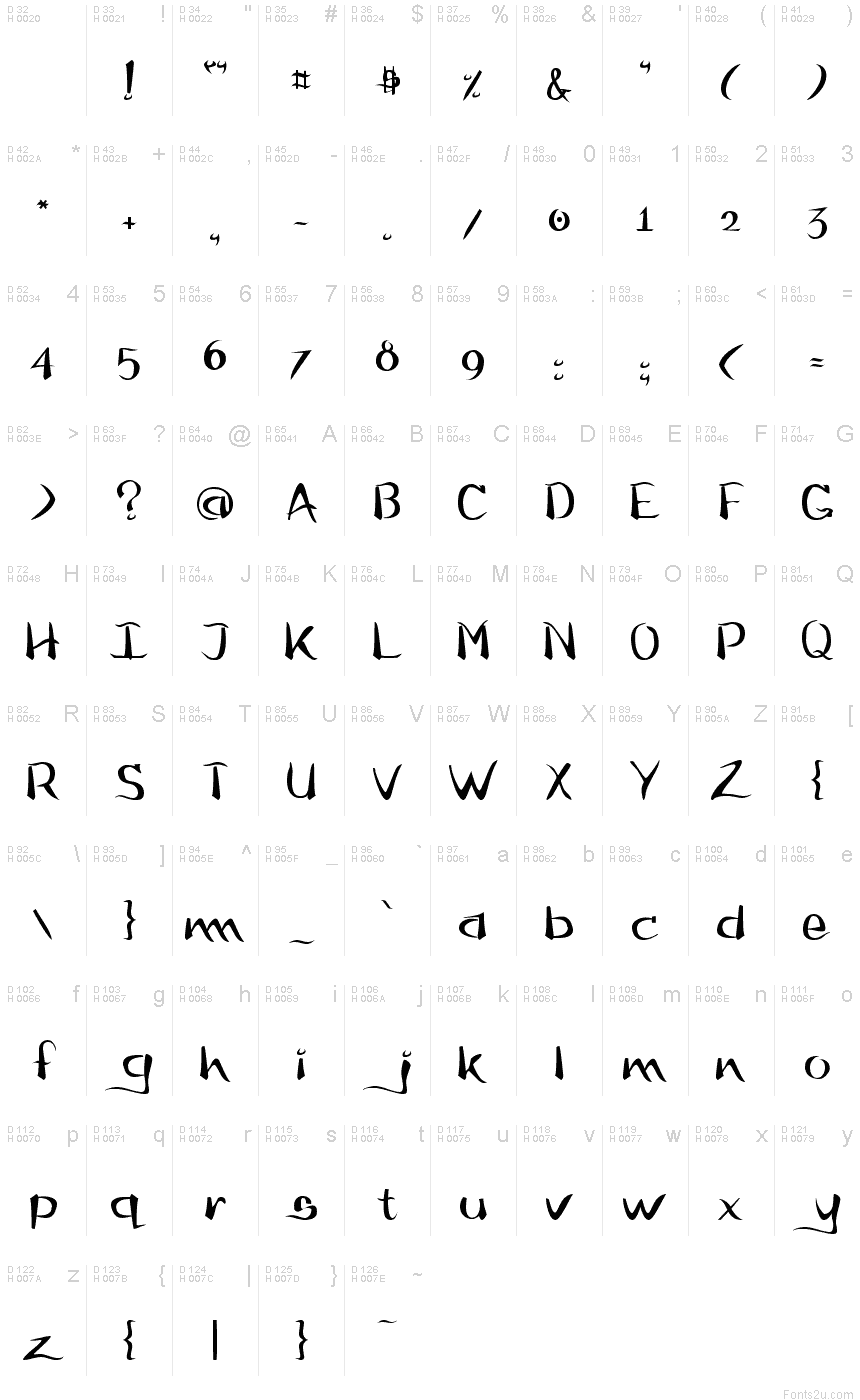
Flow autorstwa Matta Chisholma i Rolanda Bergera to darmowy krój pisma o odręcznym charakterze, który łączy w sobie luźny, malarski rytm ze spontaniczną, lecz kontrolowaną formą. Litery falują i rozlewają się jak mokry tusz na gładkim papierze, a grube pociągnięcia kończą się szybkimi, ostrymi akcentami. Dzięki zabawnej nieregularności – nic tutaj nie wygląda na mechanicznie powielane – nagłówki i logotypy sprawiają wrażenie osobistego podpisu, a nie typowego składu.
Flow nada wyrazisty charakter Twoim plakatom, okładkom albumów, ulotkom, opakowaniom, projektom okładek książek czy grafikom do mediów społecznościowych. Ten darmowy font najlepiej prezentuje się w większych rozmiarach, pozwalając atramentowym krzywiznom i dynamicznym formom w pełni wybrzmieć. Aby zachować czytelność i uziemić tę energię, w tekstach głównych warto zestawić go z czystym, geometrycznym krojem bezszeryfowym.